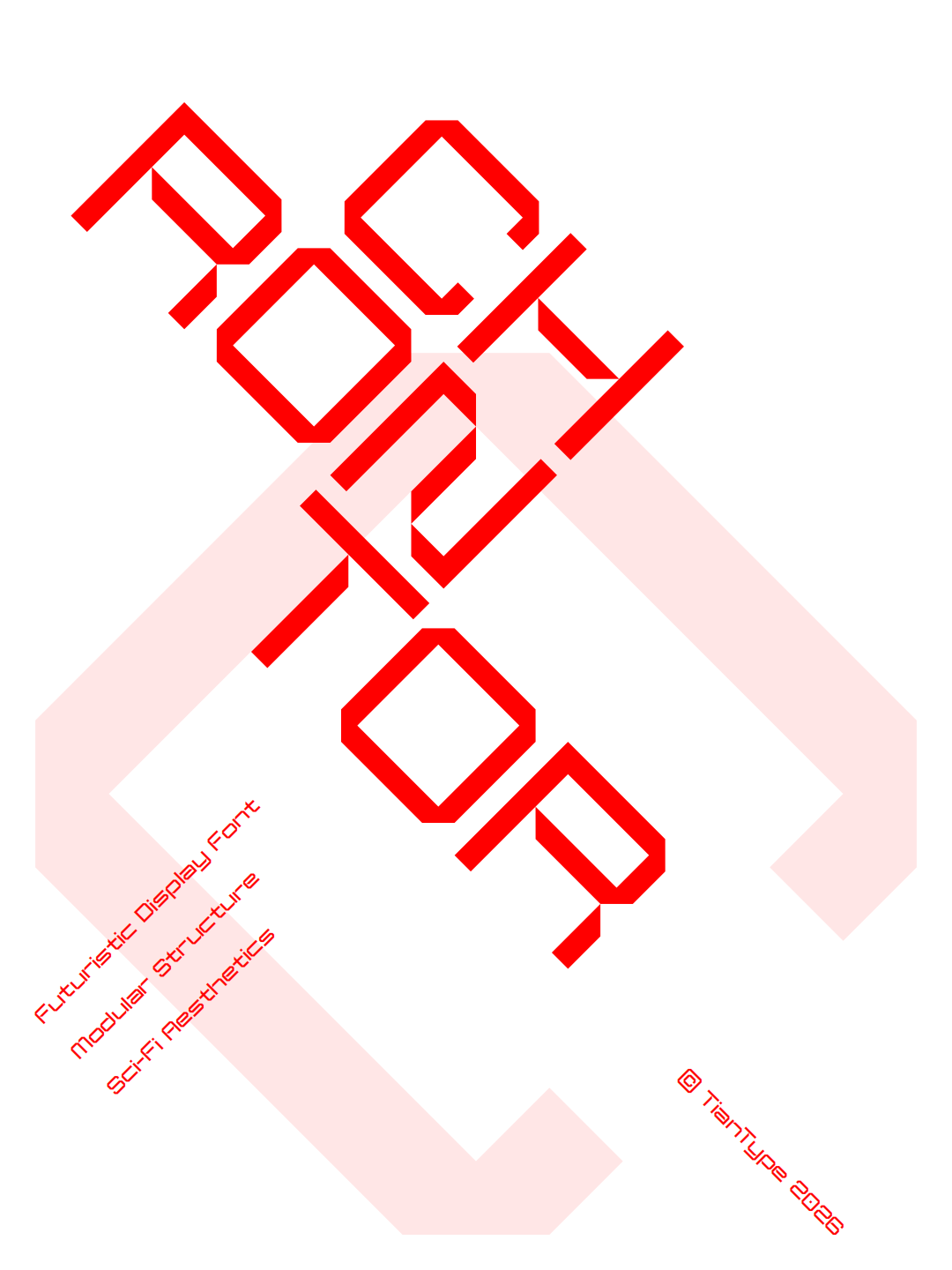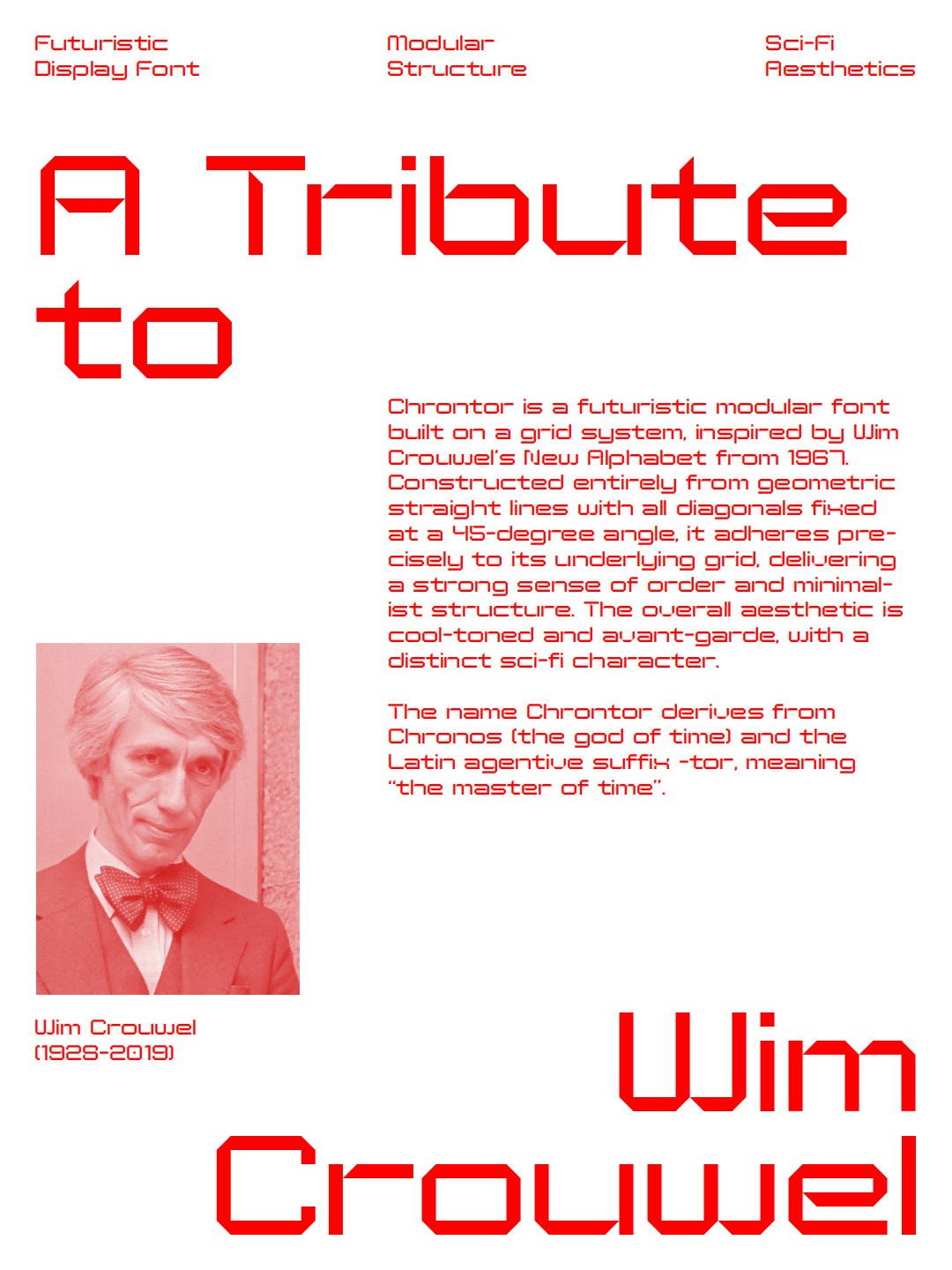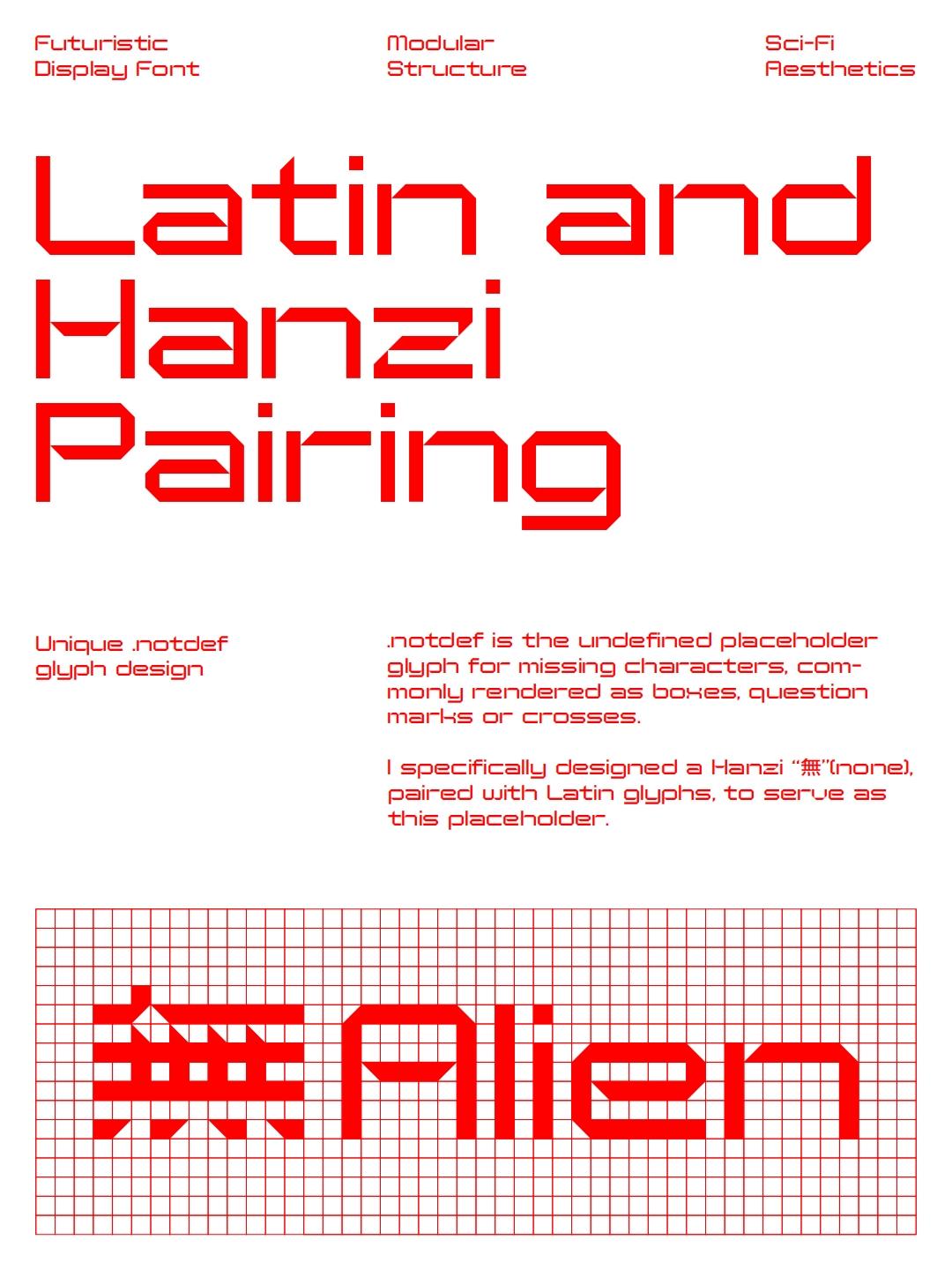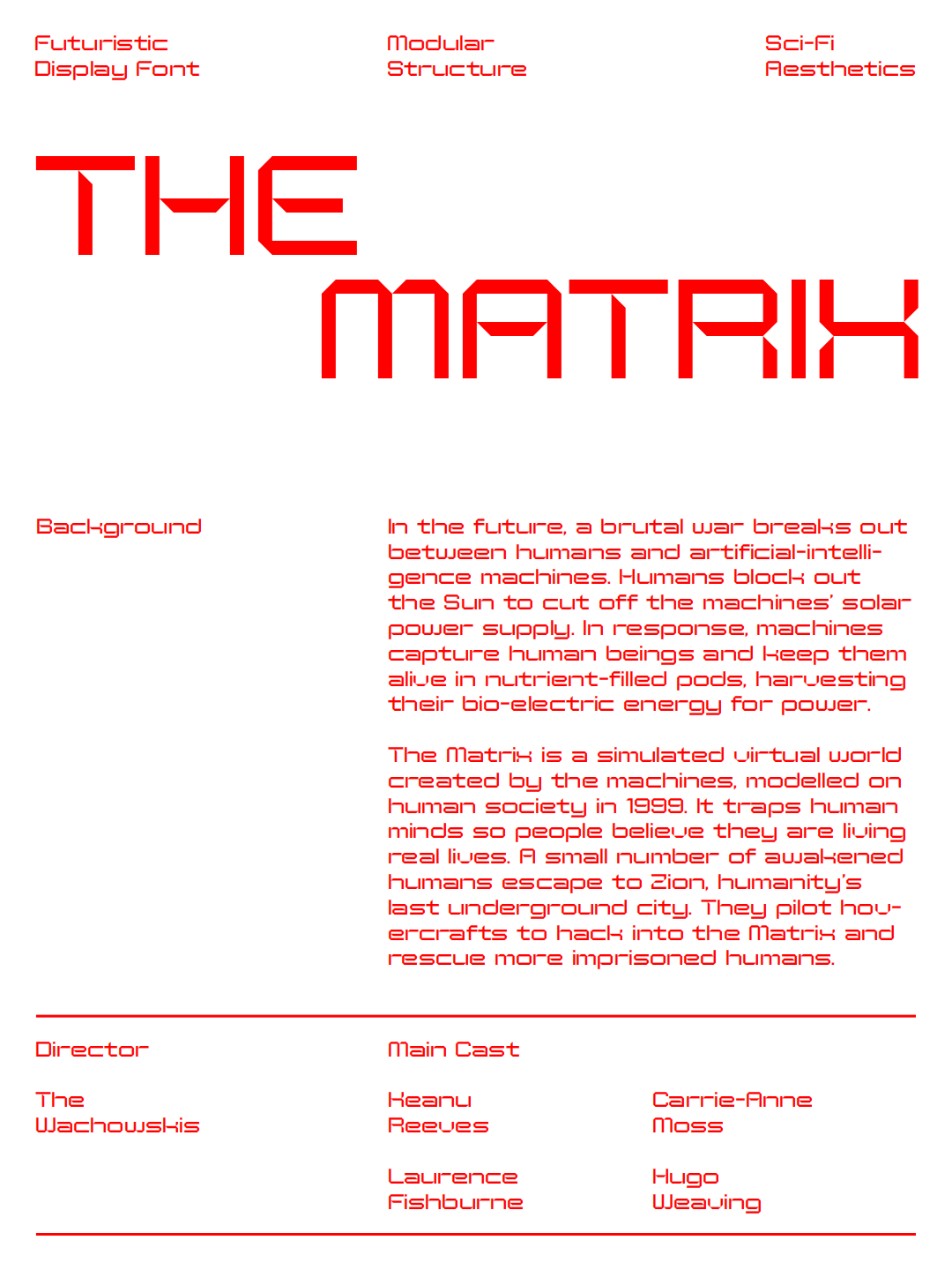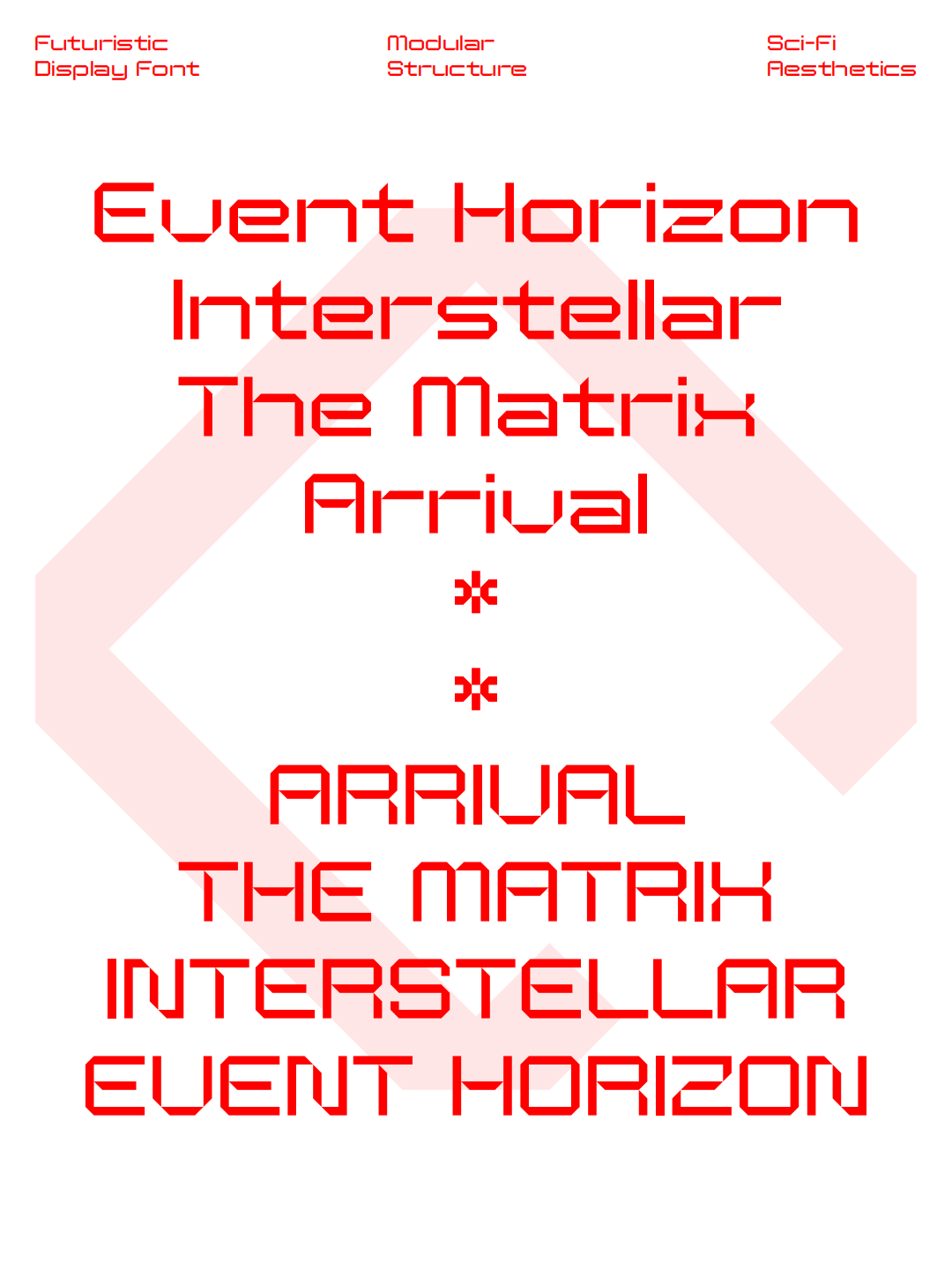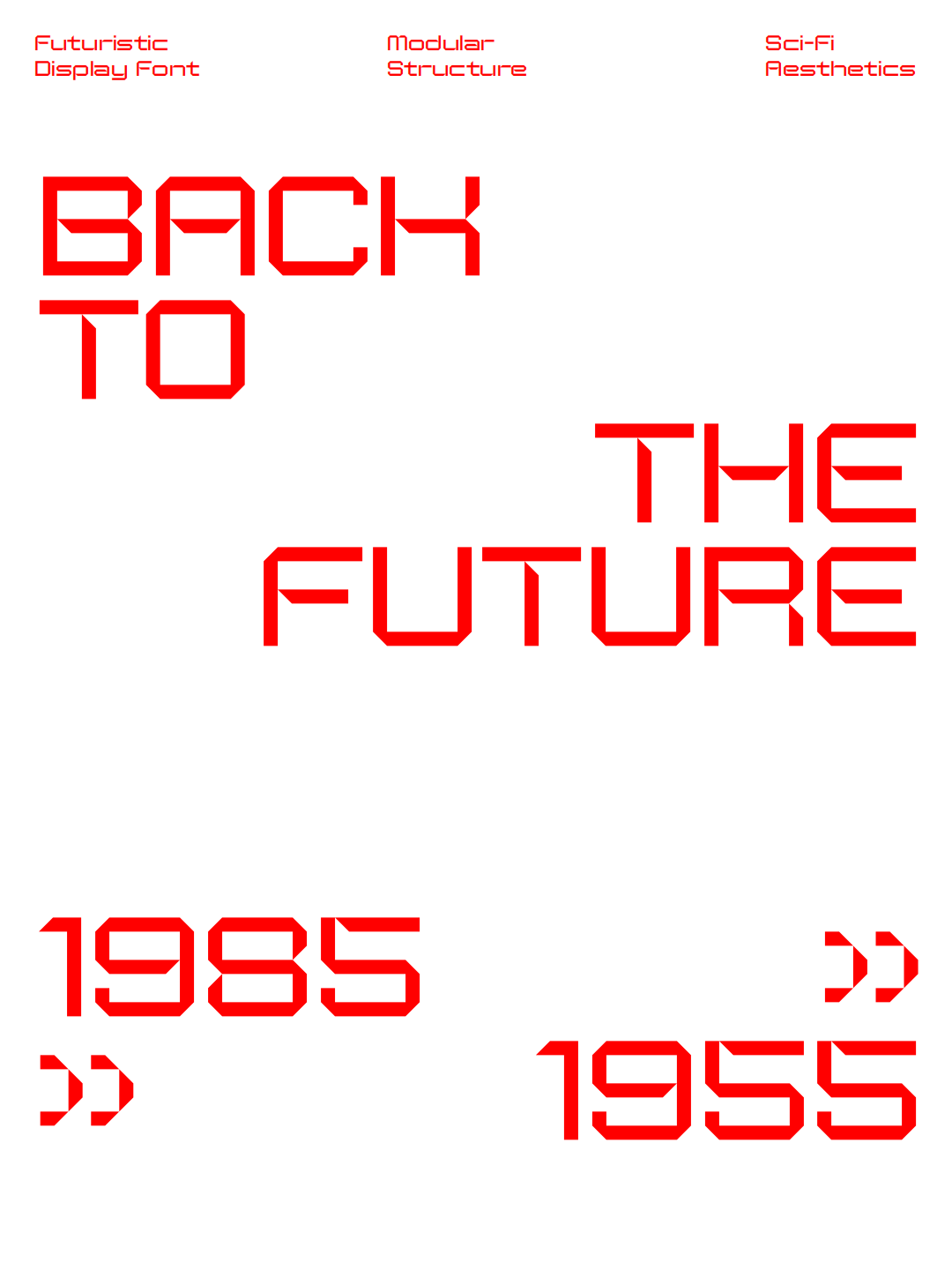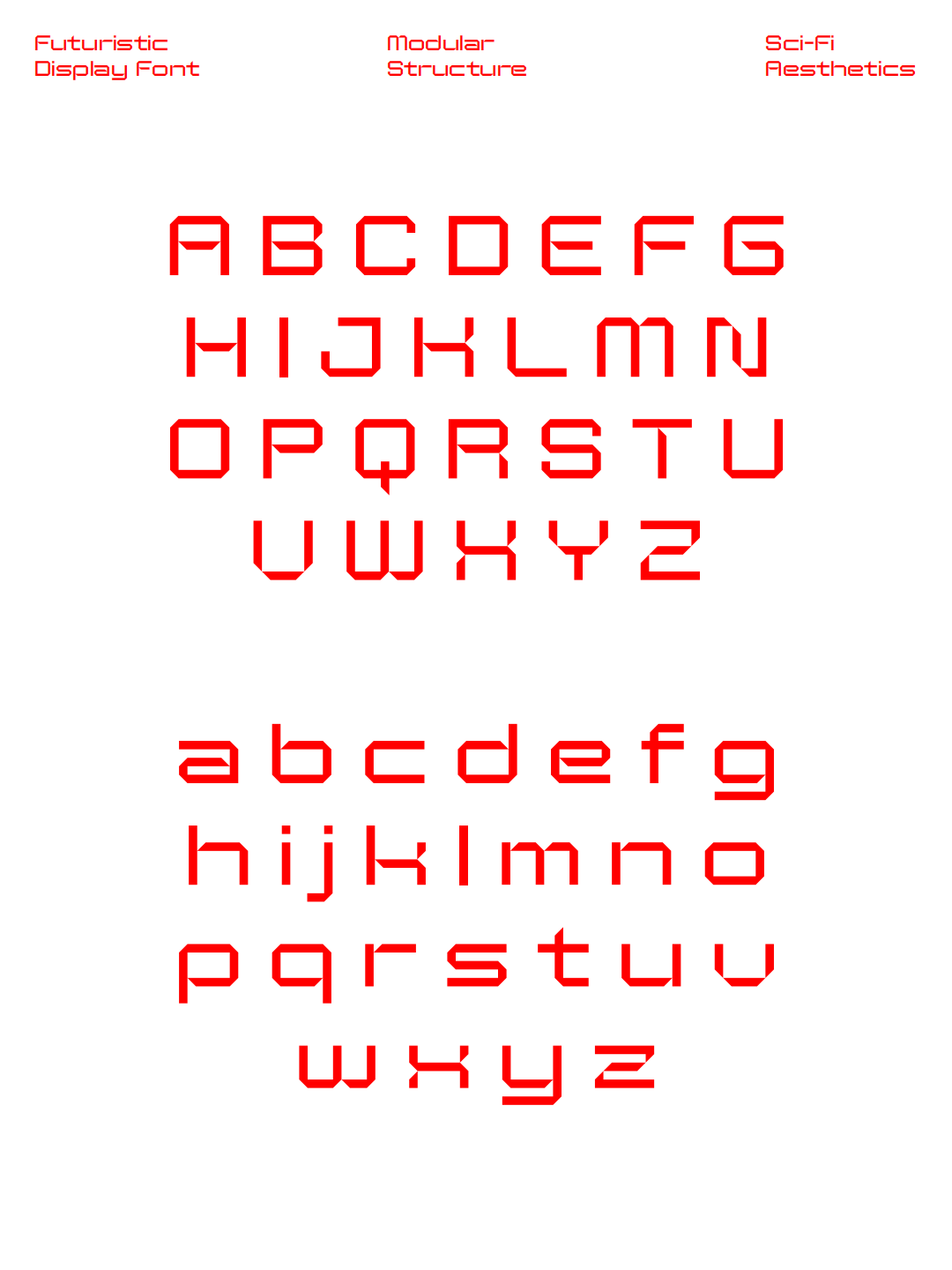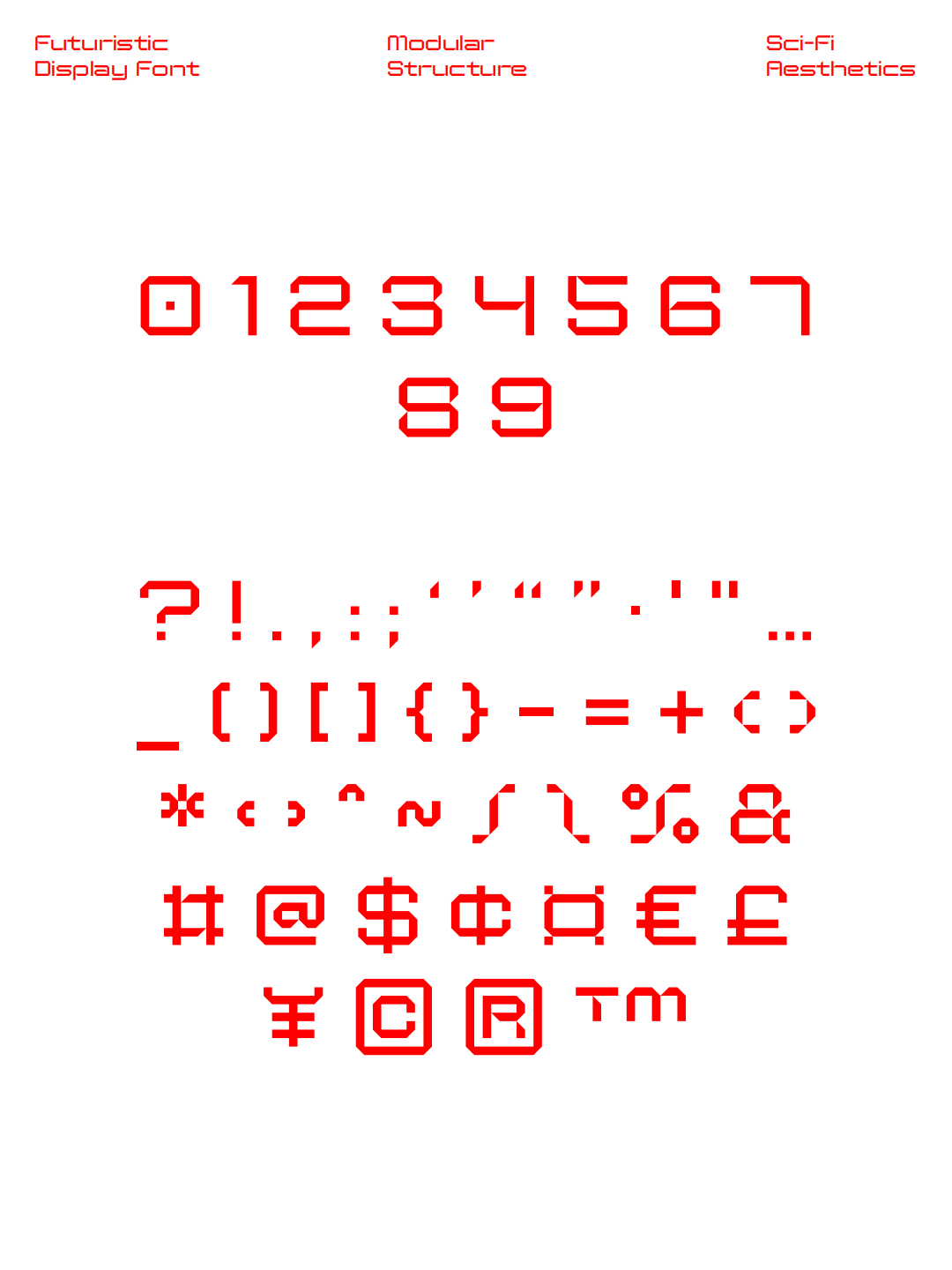
Chrontor
Chrontor是一款基于网格系统设计的未来主义模块化西文字体,由TianType设计开发,也是设计者创作的第一款西文字体。字体以几何结构为基础,通过水平线、垂直线与45°斜线进行组合,在严格的网格规则下构建出具有鲜明辨识度的字形。整体视觉简洁、冷峻且富有秩序感,同时呈现出强烈的未来主义与科幻气质。
Chrontor的设计灵感来源于Wim Crouwel于1967年创作的New Alphabet。在这一经典实验字体的启发下,Chrontor摒弃了传统西文字体中常见的自然曲线,以几何直线和切角结构重新组织字母形态。统一的45°斜线成为字体重要的视觉特征,使不同字符之间拥有高度一致的构造逻辑,也让字体呈现出类似电子显示屏、数字界面和未来机械系统的视觉效果。
在具体字形设计上,Chrontor强调模块化与结构统一。字母、数字以及标点符号均建立在相同的几何规则之上,通过断笔、切角和模块组合形成独特的字符轮廓。部分字形保留了极简的线性结构,同时通过局部变化增强辨识度,使字体既具有实验性,又能够形成完整统一的视觉语言。较大的展示尺寸能够进一步突出其几何构造,非常适合用于科幻海报、电影与游戏视觉、展览设计、品牌标识、音乐视觉、网页标题以及未来感主题的平面设计。
除了常规字符之外,Chrontor还对.notdef占位字形进行了专门设计。当用户输入字体中不存在的字符时,系统通常会调用.notdef字形进行显示,也就是设计领域中常说的“豆腐块”,常见表现形式包括方框、问号或叉号。Chrontor没有简单采用这些常见形式,而是专门设计了一枚与整体拉丁字形风格相协调的汉字「無」作为占位字形,让这一容易被忽视的字体细节也成为整个设计体系的一部分。
Chrontor这个名称源自Chronos(时间之神)与拉丁语施动后缀“-tor”,寓意“时间的掌控者”。从名称到字体结构,都延续了时间、机械与未来的设计概念。整个字体项目历时一年完成,实际投入设计制作的时间约一个月。作为TianType创作的第一款西文字体,Chrontor不仅是一次字体设计上的尝试,也体现了设计者对于网格系统、几何构成与模块化字形的探索。
总体来看,Chrontor是一款具有鲜明实验属性的未来主义西文字体。它通过严格的网格系统、统一的45°斜线以及模块化字形结构,将复古未来主义与现代科幻视觉结合起来,在极简的几何框架中营造出强烈的机械感与科技感。对于需要表现未来、数字、科技与科幻氛围的设计项目而言,Chrontor能够以独特的字形语言带来非常鲜明的视觉表现。